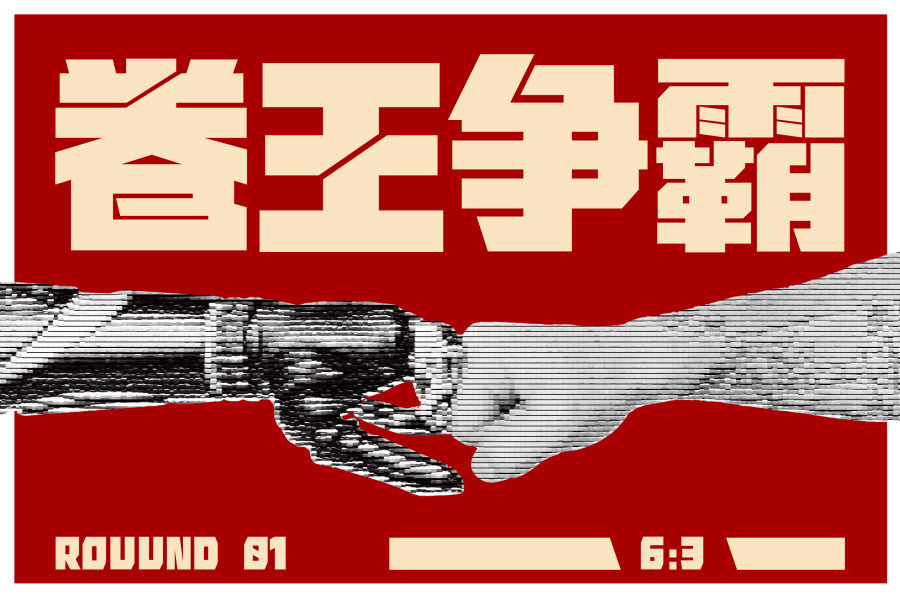
《Aa机甲黑》是一款令人惊叹的字体,它以其独特的设计元素在字体世界中崭露头角。这款字体以简单斜切的笔画和方正饱满的结构为特色,体现了机械冷静但充满力量的科技感。
字体的斜切笔画赋予了《Aa机甲黑》一种现代感和动感。这种斜切设计不仅增强了字体的视觉吸引力,还使其更适合科技领域的应用。斜切的白空间在字母之间形成了独特的叠压拼合效果,仿佛是机械结构间的精巧组合,展现出高度的工程美学。
字体的方正饱满结构为其赋予了稳重感和可读性。这使得《Aa机甲黑》不仅适用于标题和标志设计,还能在各种应用场景中表现出色,如科技产品包装、科学报告、科幻小说封面等。
《Aa机甲黑》是一款令人印象深刻的字体,它以其机械冷静与力量的完美融合,在科技领域和创意设计中有着广泛的应用前景。无论您是在寻找一种独特的字体来增强品牌形象,还是想要为您的创意项目注入现代科技感,这款字体都值得一试。